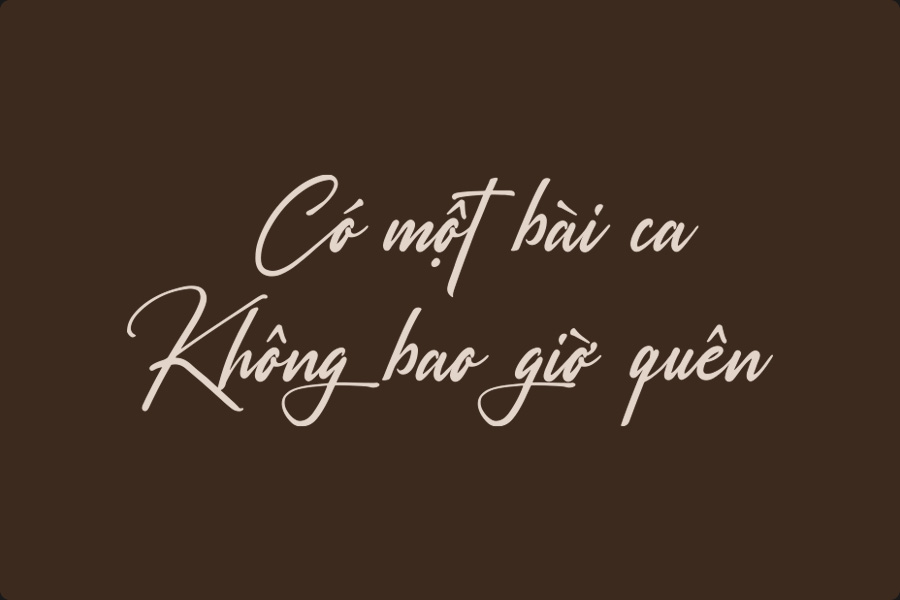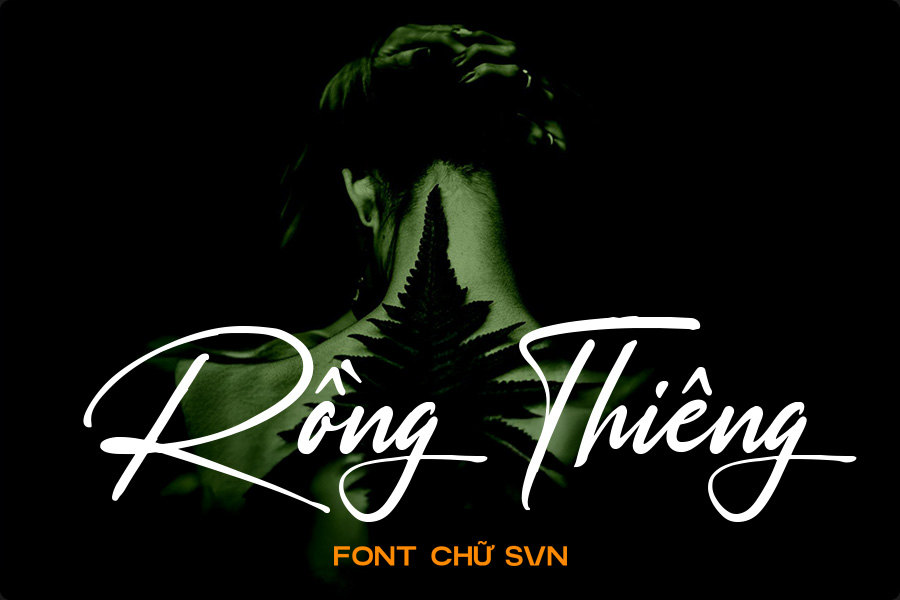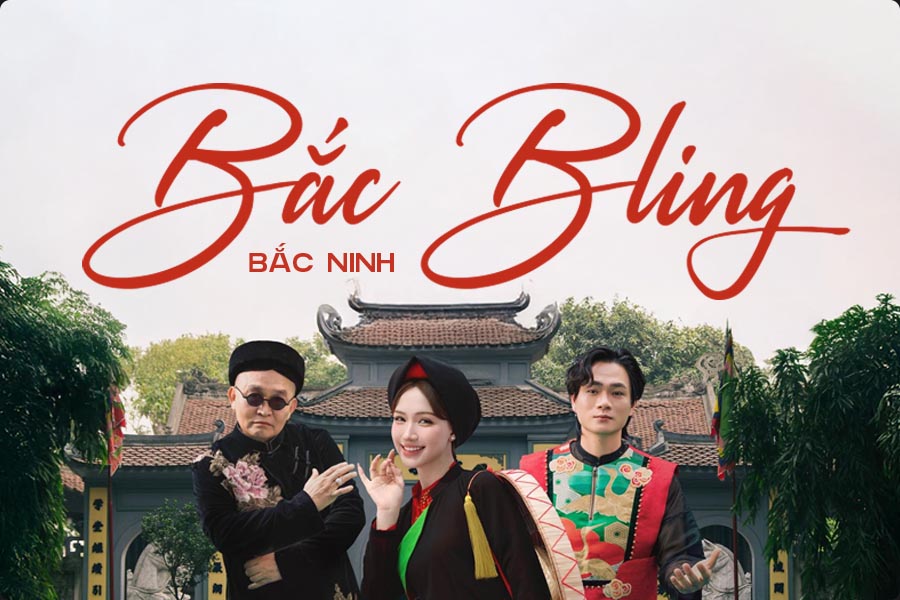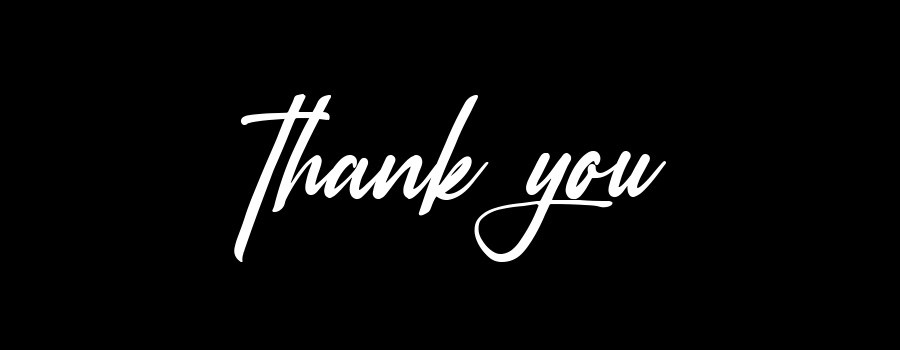
Font Chữ Miễn Phí SVN Rosellinda Alyamore Việt Hóa – Phông Chữ Ký Viết Tay Đẹp, Thanh Lịch
SVN Rosellinda Alyamore là phiên bản Việt hóa hoàn chỉnh của font chữ viết tay nổi tiếng Rosellinda Alyamore, được thiết kế gốc bởi Hanief Farandi thuộc Hanzel Space Studio. Đây là một kiểu chữ viết tay mang phong cách chữ ký (signature script), với các đường nét mềm mại, thanh thoát và đậm chất cá nhân – rất phù hợp với các thiết kế yêu cầu sự tinh tế, lãng mạn và nghệ thuật.
Phong cách thiết kế và cảm hứng
Rosellinda Alyamore được lấy cảm hứng từ những nét chữ ký tay truyền thống, với cấu trúc chữ mềm mại, đường dẫn tự nhiên và độ nghiêng nhẹ sang phải – tạo nên cảm giác như đang viết bằng bút mực thật. Font mang đến sự bay bổng nhưng vẫn đủ gọn gàng để dễ đọc, giúp truyền tải cảm xúc một cách gần gũi và chân thực.
Kiểu chữ này đặc biệt phù hợp cho các thiết kế liên quan đến:
• Thiệp cưới, thư mời, danh thiếp cao cấp
• Logo thương hiệu cá nhân, spa, mỹ phẩm, thời trang
• Trích dẫn truyền cảm hứng, tiêu đề blog hoặc nội dung mạng xã hội
Việt hóa hoàn chỉnh, đầy đủ dấu tiếng Việt
Phiên bản SVN Rosellinda Alyamore được Việt hóa tỉ mỉ bởi đội ngũ chuyên môn tại SVN Fonts, đảm bảo đầy đủ dấu tiếng Việt như ă, â, ê, ơ, ư, đ… và các thanh sắc, huyền, hỏi, ngã, nặng. Không chỉ dừng lại ở việc bổ sung glyph, font còn được điều chỉnh khoảng cách dấu và ký tự để tránh lỗi chồng, lệch hoặc rối chữ, điều thường thấy ở nhiều font chữ gốc không hỗ trợ Unicode tiếng Việt.
Việc Việt hóa giúp font trở nên sẵn sàng sử dụng cho mọi nội dung tiếng Việt, từ tên thương hiệu đến bài thơ, trích dẫn hoặc slogan mang tính cá nhân hóa cao.
SVN Rosellinda Alyamore là lựa chọn tuyệt vời cho những ai đang tìm kiếm một font chữ viết tay mang phong cách chữ ký, vừa mềm mại vừa sang trọng, lại hỗ trợ tiếng Việt đầy đủ. Với bản Việt hóa hoàn chỉnh, font này không chỉ đẹp mà còn tiện dụng, đáng tin cậy cho mọi dự án thiết kế cá nhân hoặc thương mại.